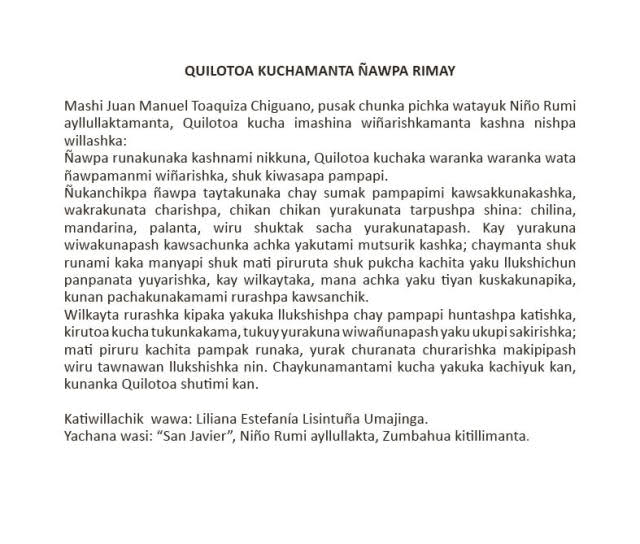
Typo für indigene Kindergeschichten
ich habe einen dieser Schnellaufträge erwischt, deadline Dienstag morgen. Es geht darum sechs Kindergeschichten und fünf Kinderlieder, alle zweisprachig (spanisch und kichwa) in einem Heftchen zu gestalten. Diese Geschichten und Lieder sind das Resultat der Aktivitäten eines interkulturellen Festes, an dem die indigenen Schulen der Cotopaxi-Region Ecuadors teilgenommen haben. Die Texte sind sehr kurz. Gestaltungsidee: Format 20 x 17 cm, eine Seite kichwa, andere Seite spanische Übersetzung, dann Doppelseite Kinderzeichnungen (die keinen inhaltlichen Bezug haben zum Inhalt, leider), wie diese hier:
Die Frage ist, welche Schrift ich für die Lieder und Geschichten und für deren Titel benutzen soll. Hab gerade Vollblockade, da das Zeug morgen fertig sein soll und ich noch mehr als genug mit den Zeichnungen zu tun haben werde. Hat irgendeine gute Seele eine Gestaltungs- oder Schriftidee bezüglich des Textes? Hier mal eine Kostprobe eines Kichwa-Textes, frisch vom Word-Dokument kopiert:
mit der Mendoza müsste der Text ganz gut kommen. Die hat schöne Antiqua-Proportionen und eine weiche Anmutung. Nebenbei ist Mendoza eine Stadt in Südamerika, wenn ich nicht irre....
Vielen Dank. Mendoza gefällt. Und ja, Mendoza liegt in Argentinien. Ich tendiere zu grosszügigem Zeilenabstand, enge Spalten. Was kann ich sonst noch tun, um alles so lesbar wie möglich zu gestalten? Wenn ich mich recht erinnere, sind die kurzen Texte vieler Kinderbücher alle fett gesetzt. Kann das jemand bestätigen? Was meint ihr zu solchen Praktiken?
linksbündiger flattersatz mit etwa 50 zeichen pro zeile und 150% ZAB müsste reichen. Die mendoza hat einen wunderbaren Mediumschnitt.
Fett ist keine gute Idee (das letzte Mal, dass ich sowas gesehen habe, war ich selbst noch Kind und da war das Buch schon angegilbt).
Mendoza sieht ganz gut aus, falls Du's lieber ohne Serifen hast, hier meine Standardtipps für solche Fälle: Fiendstar oder National (da kannst Du im OT zwischen den verschiedenen ein- bzw. zweistöckigen a und g auswählen).
Ansonsten schau mal bei Tulipan vorbei, da finde ich die Anmutung insgesamt sehr gelungen (die Schriftauswahl halte ich dort teilweise allerdings für unterirdisch, da würde ich mir kein Beispiel nehmen).
Für Typografie in Kinderbüchern – sofern die Kids nicht schon geübte Leser sind – sollte folgendes angepasst werden:
- Flattersatz sinngemäß trennen
- Laufweite erweitern
- Wortzwischenräume erweitern
- mehr Zeilenabstand als normal
- kürzere Zeilen als üblich :tutor:
Herzlichen Dank für die Tips! Wortzwischenräume erweitern erscheint mir vor allem beim Kichwa-Text (mehr als) notwendig. Ich versteh leider nur Kauderwelsch, beim Setzen ziemlich unangenehm. Und dann noch sinnvoll trennen… Soweit sind die Linguisten hier glaub ich noch gar nicht, da Kichwa erst seit kurzem geschrieben wird.